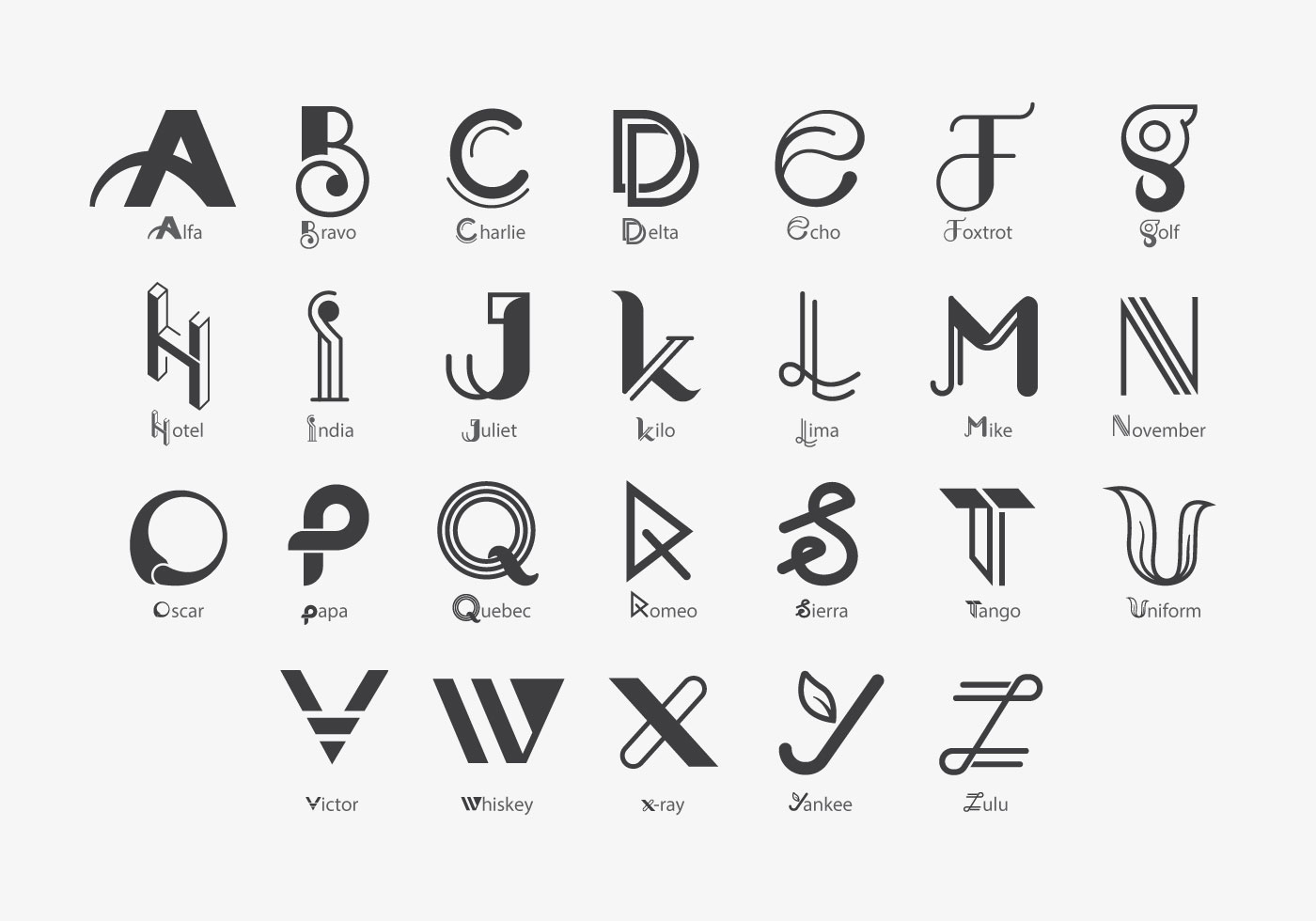
Лучший шрифт для логотипа бренда — выбрать или создать? в Блоге
ОглавлениеШрифт для логотипа — это не просто набор символов и знаков (графем) заданного размера и начертания. Каждый шрифт имеет собственный графический рисунок, которым передает настроение и характер текста. Это именно та форма, которая определяет эмоциональное содержание.
Типографика не всегда обращает на себя внимание, но обязательно оставляет впечатление от слов, которые ею написаны. Эффектность и заявка на премиальность, чувство уверенности и силы, ощущение легкости и искренности — эти и любые другие чувства, вызванные фирменным знаком, во многом определяются стилем его букв.
Поэтому шрифт для логотипа — это один из четырех инструментов (вместе с формой, символом и цветом), которые создают образ бренда для его клиентов и партнеров.
Подобрать шрифт для логотипа: с чего начать?
Каждый шрифт имеет индивидуальность и передает определенное настроение.
Чтобы решить, какой шрифт использовать для логотипа, вначале нужно ответить на базовые вопросы о позиционировании фирмы:
Можно ли в вопросе, как выбрать шрифт для логотипа, ориентироваться на пример глобальных брендов? В некоторых моментах.
Если посмотреть на логотипы всемирно известных корпораций, которые за десятилетия существования приобрели статус love-brands, то в них преобладает один и тот же шрифт — Helvetica.
Чем это объясняют маркетологи?
То что нужно для компании, которая дорожит репутацией и старается нравиться самым разным людям.Сегодня задача выбрать шрифт для логотипа из многообразия доступных может оказаться намного сложнее. Рассмотрим основные виды шрифтов и их свойства:
Если говорить о форме букв, то:
Предложив 3 тысячам респондентов оценить 100 логотипов мировых брендов, международное брендинговое агентство Siegel+Gale выяснило, что легче запоминаются четкие и простые лого.
Если говорить об особенностях восприятия, связанных с типографикой, то эмблемы с геометрическими, рублеными и гротескными графемами были названы мощными.
А шрифт для логотипа с засечками делает его традиционным и консервативным, вызывая уважение.
О чем расскажут размер и наклон букв
Прописные или строчные, курсивные, жирные или подчеркнутые — в графемах можно закодировать существенные смыслы:
Шрифт может стать выразительным и заметным элементом фирменного стиля. Иногда даже определяющим — это зависит от общей концепции айдентики: оригинальные и узнаваемые графемы приобретают большую значимость.
Выбрать шрифт для логотипа: важные правила
Выбор шрифта для логотипа нужно делать, одновременно оценивая его художественную ценность (как изображения) и функциональные возможности.
Ключевые рекомендации:
Выбирая шрифт для логотипа, не стоит ориентироваться только на тренды — они не вечны. Успешный бренд может пережить не один десяток актуальных шрифтов. Целесообразнее исходить из ценностей и позиционирования компании.
Что дает компании собственный оригинальный шрифт?
Интернет предлагает большой простор для экспериментов и много возможностей выбрать крутой и красивый шрифт для логотипа. Есть сервисы подбора, где можно оценить сотни вариантов и понравившийся шрифт для логотипа скачать бесплатно.
Но все эти наборы шрифтов — только базовый рабочий материал.
Стать инструментом для выражения сущности и характера бренда типографика может только в руках профессионала, который владеет приемами дизайна и понимает психологию его восприятия.
Типографический логотип в Illustrator и Photoshop
В этом уроке вы узнаете как оформить типографический логотип. Подобные работы сейчас в тренде и если вы любите быть в центре модных тенденций, потратьте буквально час на создание собственной работы. Такие типографические работы полезно создавать и для тренировки. Мы начнем работу в Illustrator, а закончим в Photoshop.
Шаг 1
В Illustrator создайте типографическую заготовку, используя базовые фигуры и различные шрифты. Шрифт, который использован в примере можно найти здесь.
Шаг 2
Давайте начнем с добавления эффектов. Первый из них это эффект перехода. Выделите слово New York и дублируйте его. Смените цвет нижней копии на белый, а верхнюю надпись оставьте темного цвета. Выделите обе копии и в меню выберите Object>Blend/Объект>Переход.
Укажите 4 px в качестве расстояния между шагами (Specified Distance).
Шаг 3
Таким же способом создайте диагональные линии для орнамента левой разделительной линии.
Шаг 4
Выделите самую верхнюю надпись и в меню выберите Object>Envelope Distort>Envelope with Warp/Объект>Искажение оболочки>Деформация. Используйте стиль Arc/Дуга с параметрами как показано ниже.
Шаг 5
Повторите то же с нижней надписью.
Шаг 6
Выделите прямоугольник и текст, из которого создана ленточка и также примените к ней Object>Envelope Distort>Envelope with Warp/Объект>Искажение оболочки>Деформация. На этот раз укажите иные настройки, как показано ниже.
Шаг 7
Вот что получится в итоге.
45. Cooper Hewitt
Дизайнер: Chester Jenkins
Современный шрифт без засечек — это именно то, что доктор прописал Смитсоновскому музею дизайна Cooper Hewitt после того, как они решили обновить его. Как и здание, символы этого шрифта наполнены геометрическими кривыми и арками. Его четкие буквы представлены в 14 стилях и отлично подходят для логотипов, которые хотят передать профессионализм и надежность.
46. Lust
Дизайнер : Neil Summerour